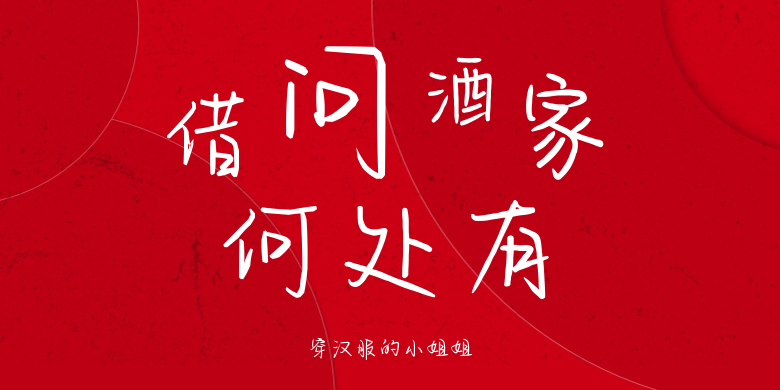
穿汉服的小姐姐
穿汉服的小姐姐,这款字体结构工整、笔画清晰,兼顾美观与易读性,适用于标题、正文、海报、包装、LOGO 等多种场景。字形优雅稳定,风格百搭耐看,适配日常排版与创意设计,让文字呈现更舒适、更具质感。穿汉服的小姐姐一笔一画,皆是细节,以均衡的比例、流畅的线条打造舒适视觉体验,字形端正大气,风格简约现代。无论是商业设计、品牌宣传还是日常排版,都能轻松驾驭,让文字更有格调与力量。穿汉服的小姐姐字体下载。